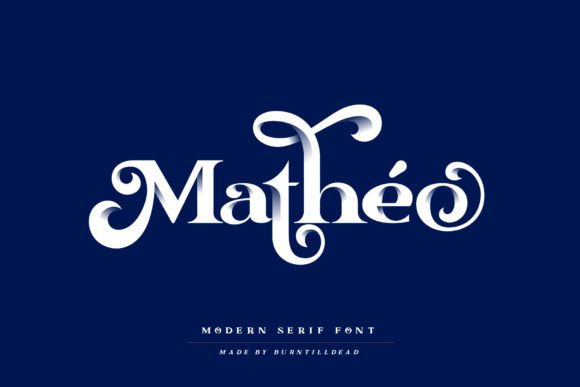
Creativefabrica Matheo Font 2021
[Creativefabrica] Matheo Font (2021)
Matheo - смелый, современный и высоко детализированный шрифт с засечками.
Влюбитесь в его восхитительный стиль и используйте его для создания великолепных дизайнов!